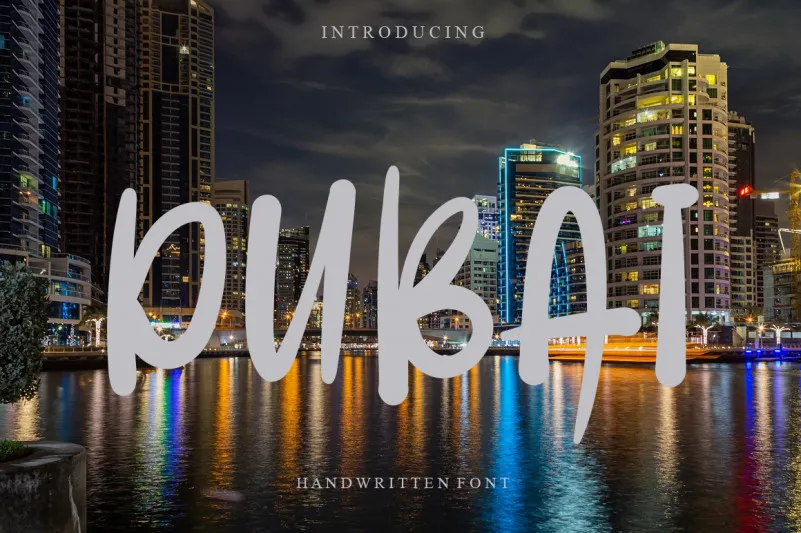
Dubai Font – Fonte Grátis
Dubai Font
Esta é uma fonte cursiva suave e genuína criada para dar aos projetos um toque relaxado e alegre. Ideal tanto para designs digitais quanto impressos, esta fonte irá adicionar um toque descontraído e moderno à sua próxima criação. Perfeita para gráficos de newsletter, design de aplicativos ou até mesmo estampas de roupas, essa fonte certamente dará um charme especial a qualquer projeto que você desenvolver. O designer LevinCreative trouxe uma sensação amigável e jovial à esta fonte, garantindo um visual agradável e versátil para designers de todo o mundo. Engaje-se e descubra como essa font pode transformar seus projetos em verdadeiros trabalhos de arte.